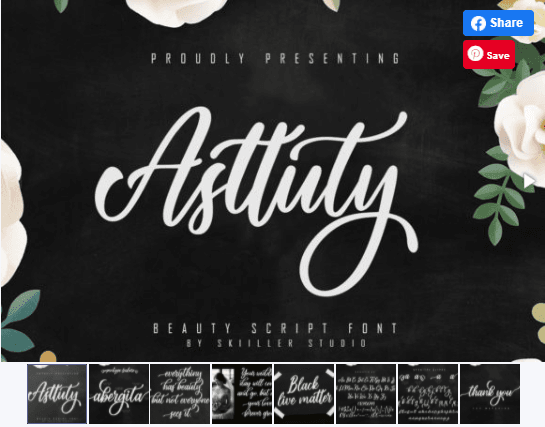
Asttuty Script Font
Asttuty Script - это элегантный шрифт с современной атмосферой и безупречной формой, вдохновленный вневременной классической каллиграфией. Asttuty Script имеет кодировку PUA, что означает, что вы можете легко получить доступ ко всем глифам и росчеркам!